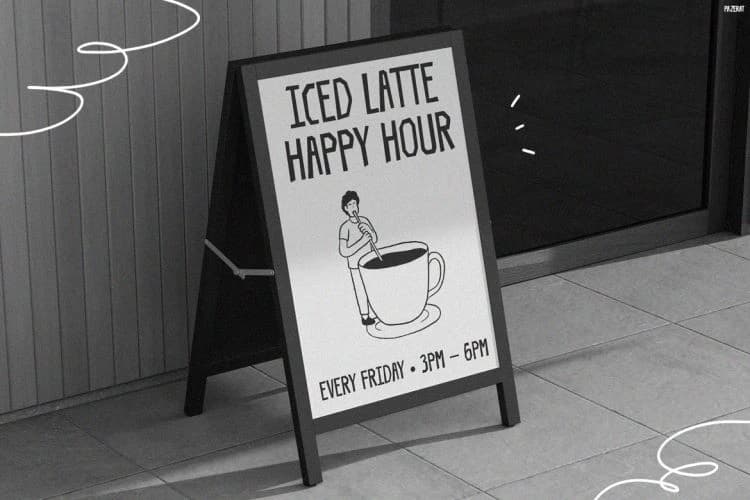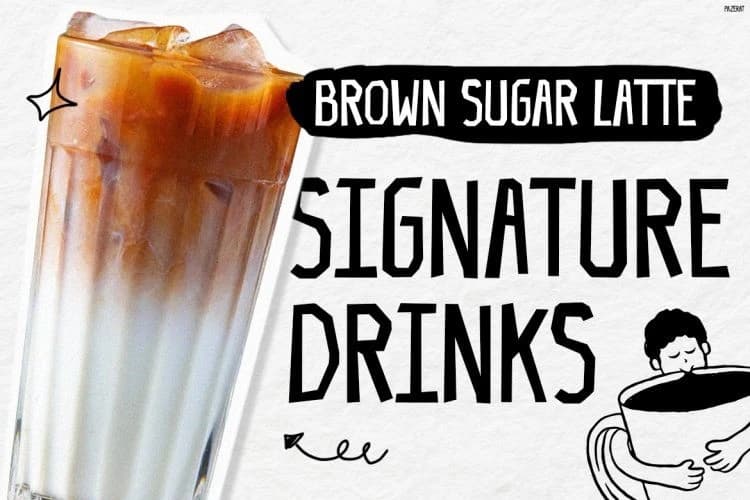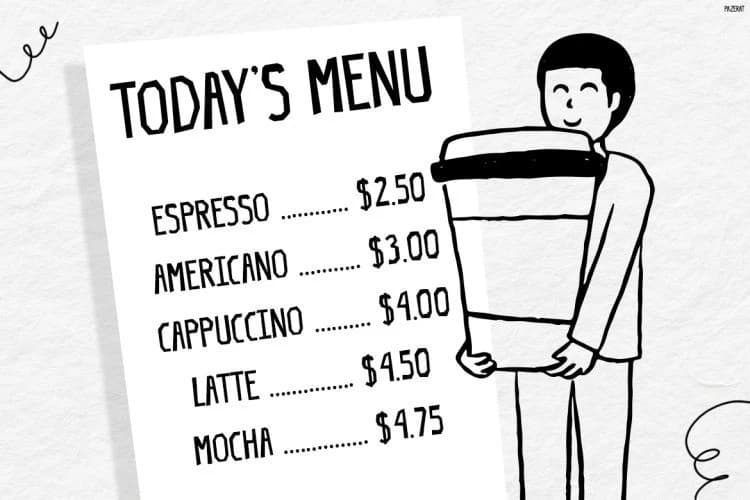
Pazerat Eğlenceli Yazı Tipi
Pazerat Playful Font, samimi kahve dükkanlarından, kafe kültüründen ve oyuncu el yapımı tipografiden esinlenen cesur bir el yazısı gösterim yazı tipidir. Uzun harf biçimlerine sahip, karalamaya benzer detaylar ve ham el yazısı enerjisiyle tasarlandı.
Pazerat Playful Font, samimi kahve dükkanlarından, kafe kültüründen ve eğlenceli el yapımı tipografiden ilham alan kalın bir el yazısı gösterim yazı tipidir. Uzun harf biçimleri, karalama detaylar ve ham el yazısı enerjisiyle tasarlandı